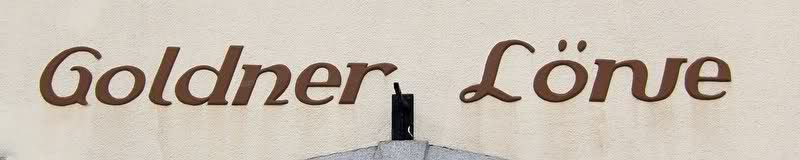
Seltene Buchstabenform
bin dieser Woche dreimal an einem Wirtshaus vorbeigefahren.
Altvertrauter Name, aber was ist mit dem "w" (grrrh, das man erst nach Anzeige des ganzen Bildes sieht ...) passiert?
ganz schön avantgardistisch :hammer:
ich glaube, manchmal denken die Leute nicht weiter drüber nach. Letztens hatte ich eine PDF für ein Plakat bekommen, in der sämtliche Umlaute anstatt in einer Futura in einer fetten Verdana oder Tahoma gesetzt wurden. Hab natürlich angerufen … »Absicht!!!«.
Kam raus, dass es einen Fehler mit der Schrift gab (Futura-Klon) und die dann das Ergebnis gut fanden, weil dann ja die Leute hingucken.
Ich würde da nicht zu viel reininterpretieren. Typofundstück allemale ;)
Das „w“ wurde in Anlehnung an die früher gebräuchliche Form-Variante der Lateinischen Schulschrift gestaltet. Für viele ist diese Form nicht bekannt, da es sich eben um eine heute nur noch selten zu findende Variante handelt. Es gab in der Lateinischen Schreibschrift zwei verschieden „w“.
Also: nicht avantgardistisch sondern nostalgisch.
Das „w“ wurde in Anlehnung an die früher gebräuchliche Form-Variante der Lateinischen Schulschrift gestaltet. Für viele ist diese Form nicht bekannt, da es sich eben um eine heute nur noch selten zu findende Variante handelt. Es gab in der Lateinischen Schreibschrift zwei verschieden „w“.
Also: nicht avantgardistisch sondern nostalgisch.
Und: eher österreichisch als lateinisch, richtig? :)
Ich sehe es gerade hier:
Ist mir noch nie zu Gesicht gekommen.
Aber auch bei uns gab (gibt?) es beidei Varianten.
Ich meine mich erinnern zu können dass ich jenes w auch schon in Schwaben gesehen habe. Wenn ich mir die Kurrentschrift so anschau könnte das durchaus eine Ableitung daraus sein.
Die Form geht auf die gebrochene Schrift zurück. Dort ist es üblich, daß im w die beiden ersten Stämme oben und nicht unten verbunden sind. Beim y ist es genauso. Als Beispiel die Kleist-Fraktur:
Mit Österreich hat das also nichts zu tun. (Außer vielleicht, daß die Form dort durch die Schulschreibschrift möglicherweise etwas bekannter ist.)